¿Qué sucede cuando el diseño gráfico y la tipografía se cruzan en el camino de una estudiante de ingeniería mecánica? El caso de Beatriz Lozano es realmente interesante por los factores que se entremezclan: su activismo a favor del derecho de los inmigrantes hizo que experimentara de primera mano la verdadera dimensión de la comunicación visual. Y tal fue el impacto que dejó la ingeniería y acabó graduándose en la Escuela de Arte y Diseño de la Universidad de Michigan en 2016. El diseño gráfico y la tipografía pueden ser armas muy poderosas.
Aunque su formación como ingeniera tal vez constituya uno de los grandes impulsos que la llevan a investigar «cómo la codificación y el movimiento pueden impulsar las formas de la tipografía en nuestro mundo digital».
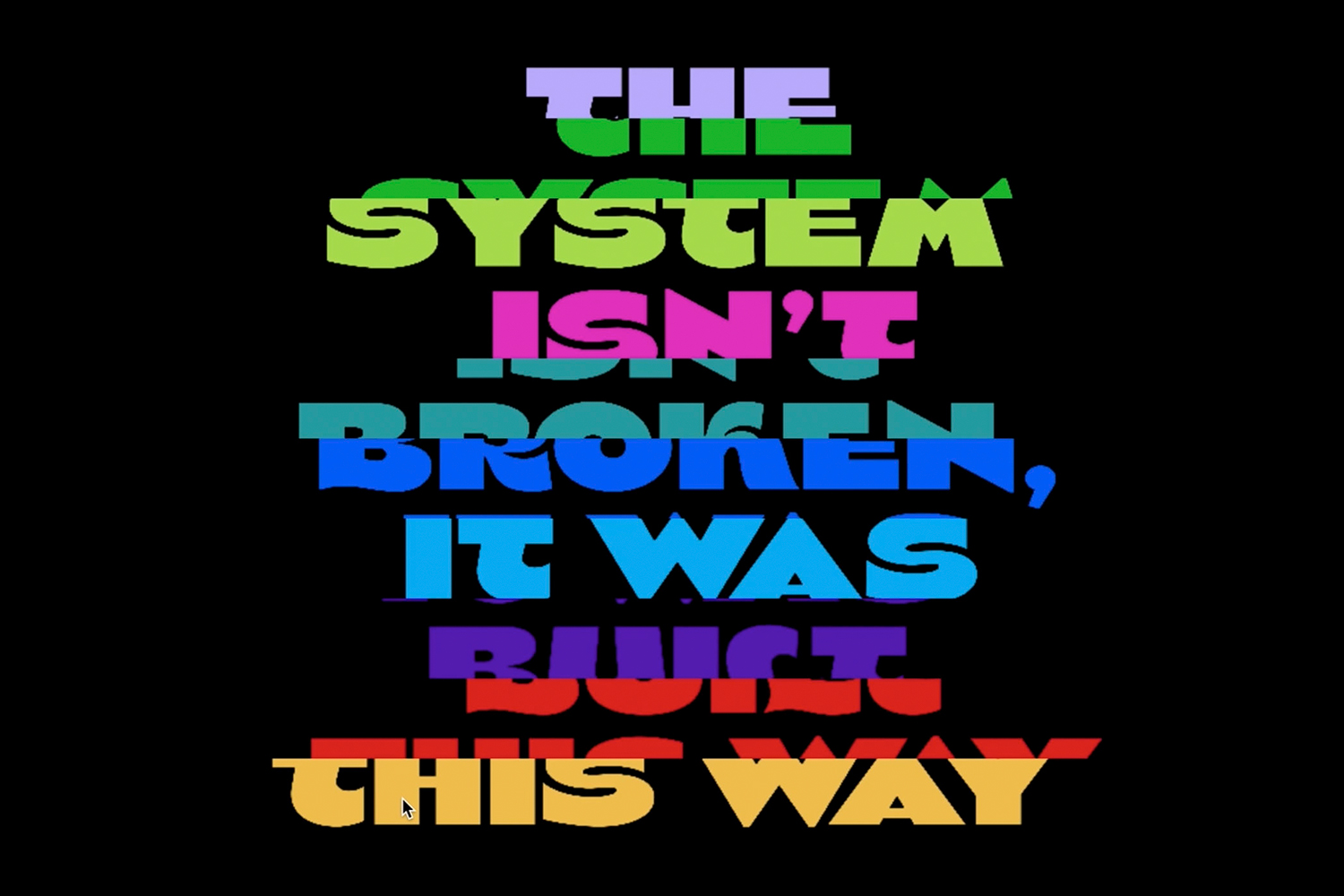
En su fascinante universo creativo, como muchas jóvenes diseñadoras y diseñadores de su misma generación, la tecnología digital no es una mera herramienta con la cual alcanzar un fin, sino un componente determinante tanto en el proceso como, por supuesto, en el resultado.
El camino hacia la tipografía
Residente en Nueva York, en la actualidad es directora de diseño en Sunday Afternoon, un estudio donde se dedica a diseñar identidades visuales tipográficas, y profesora en Parsons School of Design. Pero los inicios nunca son sencillos. Nada más instalarse en la Gran Manzana, «atendí bastante charlas y conferencias de diseño abiertas al público, donde muchos de los oradores eran diseñadores tipográficos. Esta exposición a los diseñadores contemporáneos me inspiró a tratar de comenzar a aprender diseño tipográfico por mi cuenta.
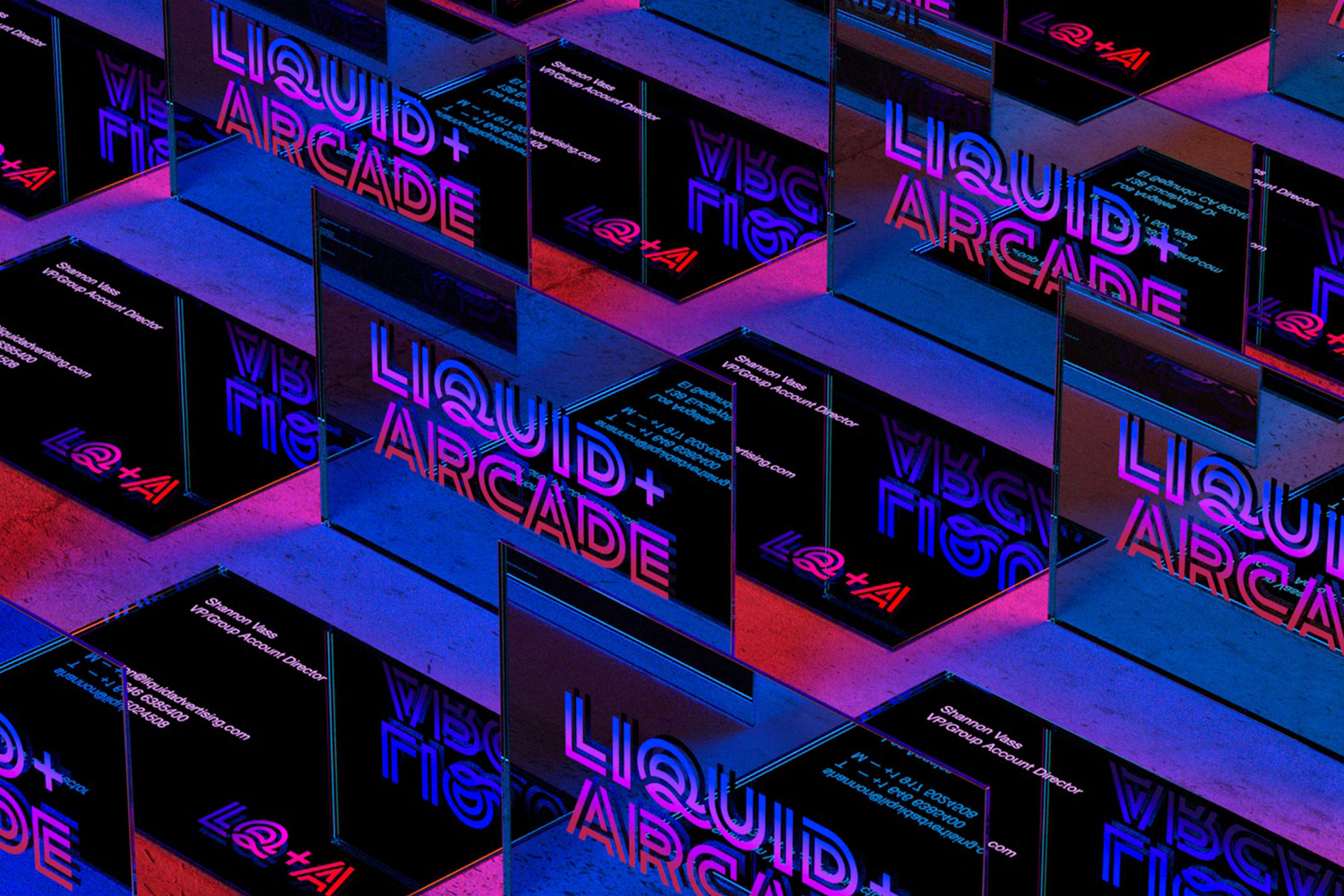
»En ese tiempo, todavía era una pasante de diseño que apenas pagaba mi renta, por eso asistir a un programa formal de diseño tipográfico no era ni remotamente una posibilidad para mí. Empecé a comprar libros sobre diseño tipográfico y comencé a escribir ideas para fuentes potenciales. En 2018, compartí estas exploraciones en un evento TypeThursday, donde recibí críticas útiles y comencé a conectarme con diseñadores tipográficos expertos. Desde entonces, siento que soy muy afortunada por encontrar mentores en la comunidad de diseño tipográfico que me han ayudado a aprender y crecer».
Las raíces de la vocación tipográfica
Lo lúdico está muy presente en el trabajo de Beatriz. Su afán experimentador es su lenguaje natural. La creatividad no conoce fronteras entre afrontar una identidad visual y un lettering interactivo proyectado por toda la ciudad de Nueva York durante las protestas de 2020. Pero convertirse en la diseñadora que es hoy en día no es sencillo. «Durante mis primeros dos años en la ciudad de Nueva York, estuve trabajando en proyectos de diseño gráfico, muchos de los cuales eran trabajos de producción.
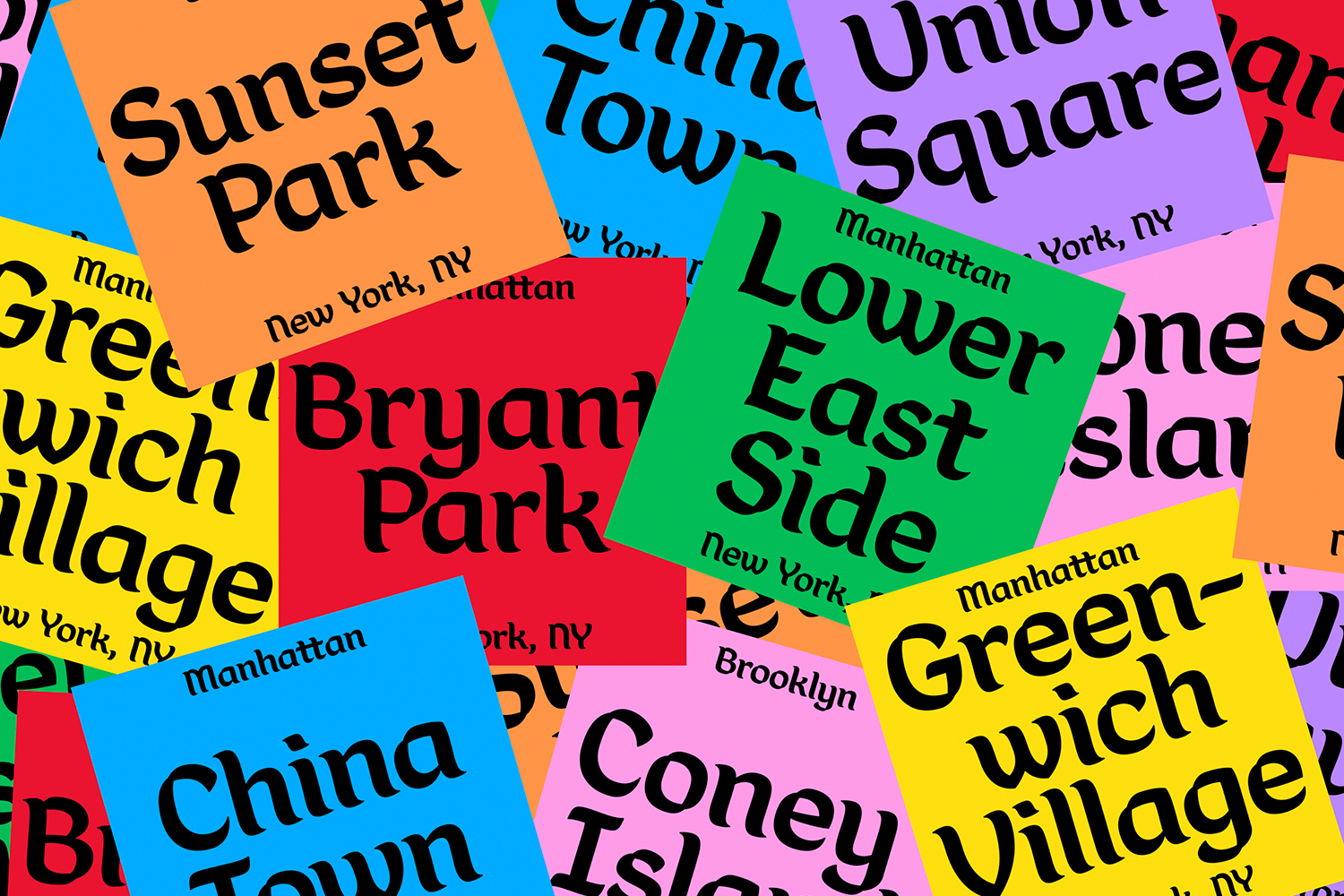
»En las noches, después del trabajo, y en los fines de semana, comencé a escribir letras y a intentar aprender a diseñar una tipografía por mi cuenta. Pero no fue hasta 2019 que tuve el privilegio de ser diseñadora residente en Morcos Key, un estudio cofundado por el diseñador tipográfico Wael Morcos. Fue mi primer mentor de diseño tipográfico y me ayudó a aprender los fundamentos. A partir de ahí, aprendí de mi actual director creativo, Juan Carlos Pagán, quien me guió mientras diseñaba y cuando publiqué mi primera tipografía, Ancho, en 2020.»
Tecnología emocional
«Mi relación con la tipografía tiene sus raíces en la exploración. Estoy explorando cómo la codificación y animación pueden impulsar las formas en que existe la tipografía en nuestro mundo digital. El año pasado lancé Java Sans, una tipografía interactiva diseñada en P5, y actualmente estoy trabajando en una tipografía basada en realidad aumentada.»
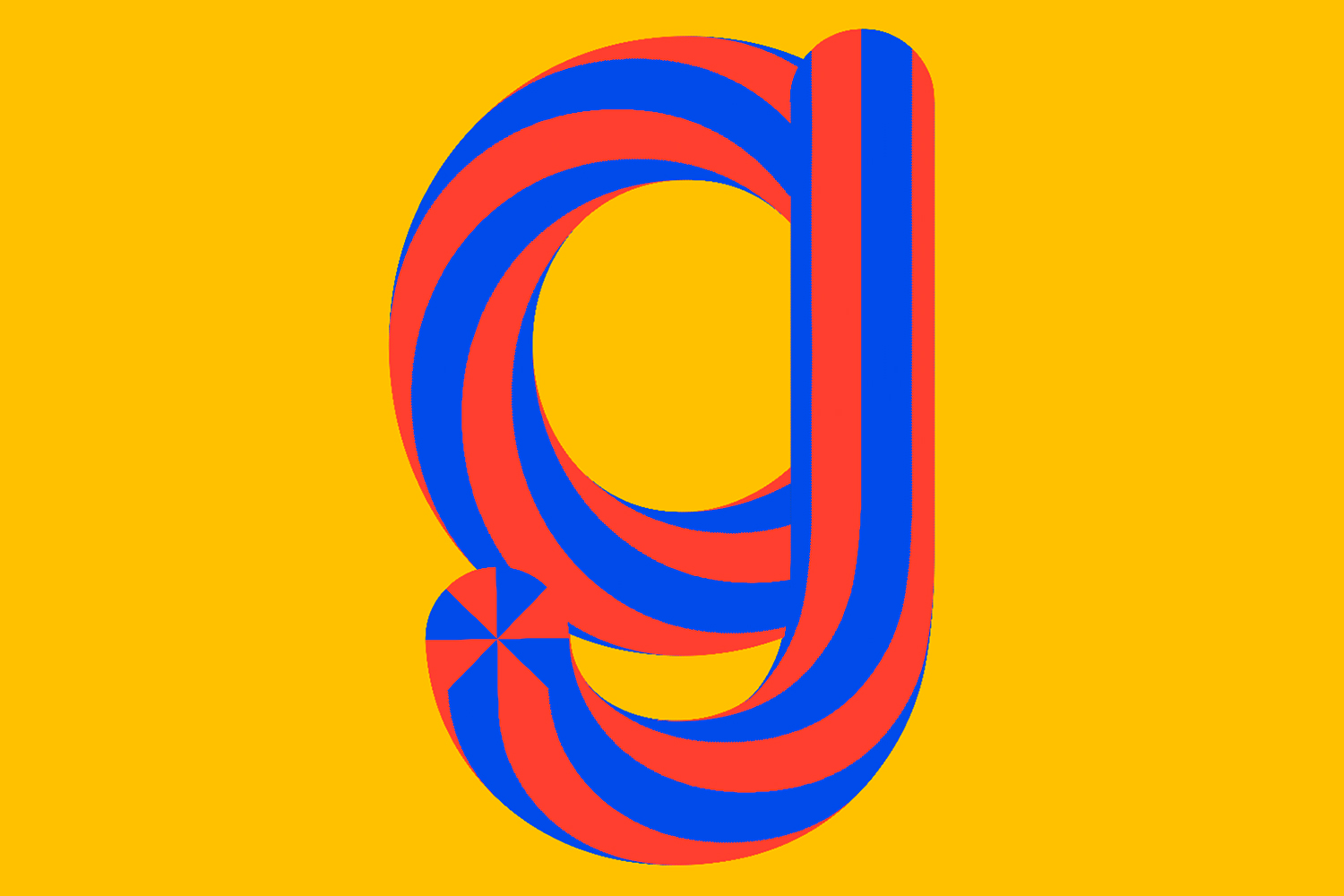
Actualidad tipográfica
«Creo que el diseño tipográfico se está volviendo más accesible, especialmente después de la pandemia, porque muchas clases y conferencias se volvieron virtuales, lo que significa que cualquiera puede asistir. Estos últimos años hemos visto un crecimiento exponencial en los jóvenes diseñadores que están aprendiendo diseño tipográfico.»
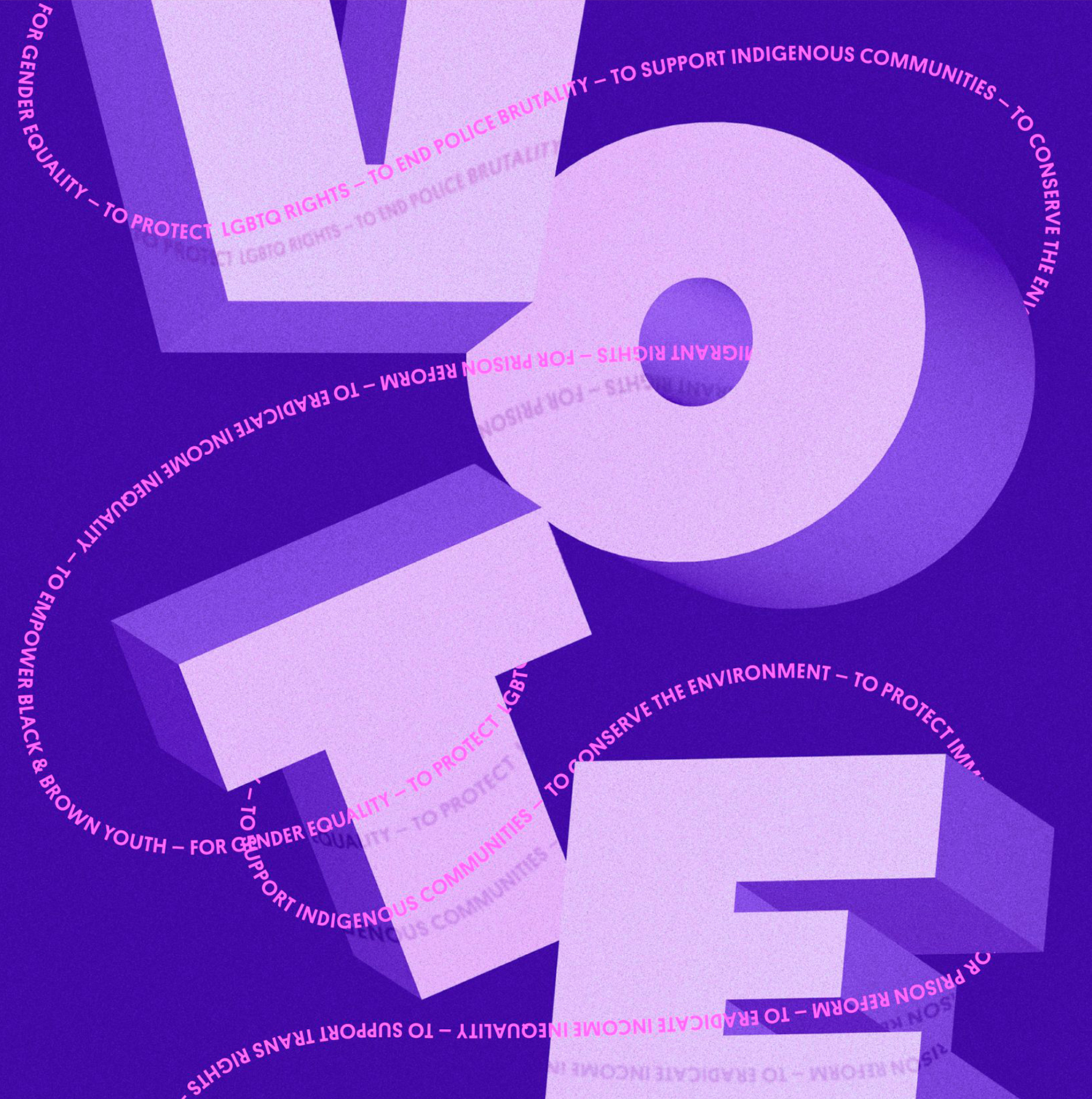
El futuro más allá del alfabeto latino
«Lo que más me interesa es ver cómo esta nueva accesibilidad seguirá haciendo posible que los diseñadores de todo el mundo, especialmente de culturas y identidades subrepresentadas en el ámbito de tipografía, puedan ahora diseñar tipos de letra para sus propias comunidades en sus lenguaje primarios.»